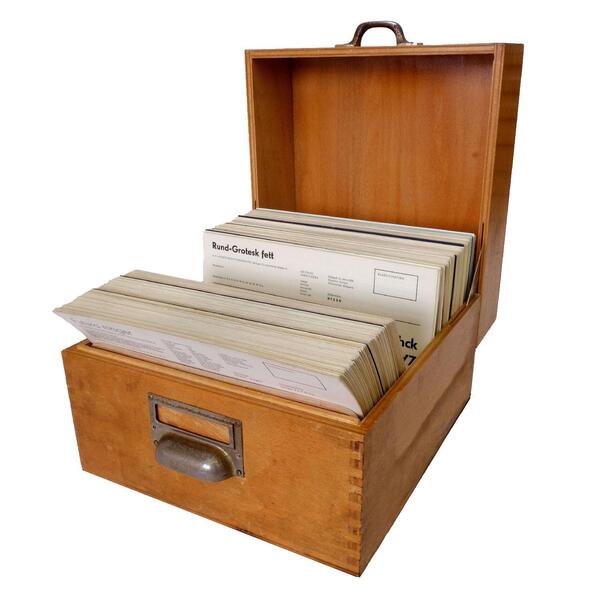
Ein Schriftmustersammlung mit Bleisatz-Mustern der westdeutschen Schriftgießereien Bauersche Gießerei, H. Berthold AG, Genzsch & Heyse, Ludwig & Mayer, D. Stempel AG, Johannes Wagner GmbH, und C. E. Weber. Initiiert und verlegt vom Verein Arbeitsgemeinschaft der gra­phischen Verbände des deutschen Bundesgebietes entstand zwischen 1958 und 1970 ein Kasten mit A5-großen Karten, 638 Schriften, gesetzt und gedruckt in einer weitgehend einheitlichen Gestaltung.
Prof. Michael Wörgötter von der Hochschule Augsburg nahm sich 2023 der Sammlung an und untersuchte sie eingehend. Es entstand ein Nachdruck in zunächst kleiner Auflage mit einer zusätzlichen Publikation, die Hintergrundinformationen liefert.
Die angefertigten Scans der Karteikarten sind nun über ein Flickr-Album des Letterform Archives San Francisco dauerhaft abrufbar. Im Gegensatz zu herkömmlichen, werblichen Schriftmustern zeigen die Karteikarten auf einen Blick den kompletten Zeichensatz und liefern verlässliche Zusatzinformationen wie das Erstgussjahr.